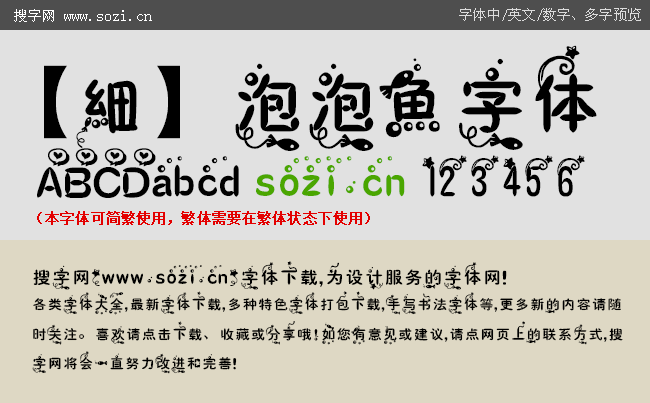
細泡泡魚字體
搜字網(wǎng)給大家提供一款細泡泡魚字體手機中文字體下載。這款手機中文字體以漢儀橄欖體為原形,在筆畫間嵌入有趣的卡通泡泡和小魚的圖形,漢儀橄欖體兩頭尖,中間呈凸圓弧形。筆畫簡潔新穎,柔軟流暢,風(fēng)格稚氣質(zhì)樸,明快清純,藝術(shù)性較強。加入卡通圖案后更加有趣,非常適合喜歡卡通的朋友在手機上安裝使用。